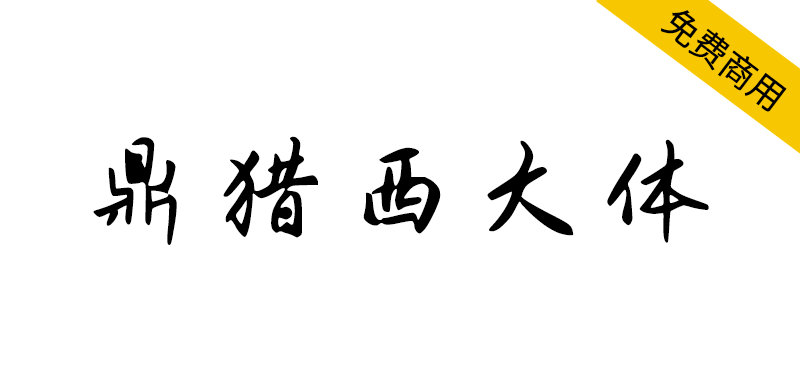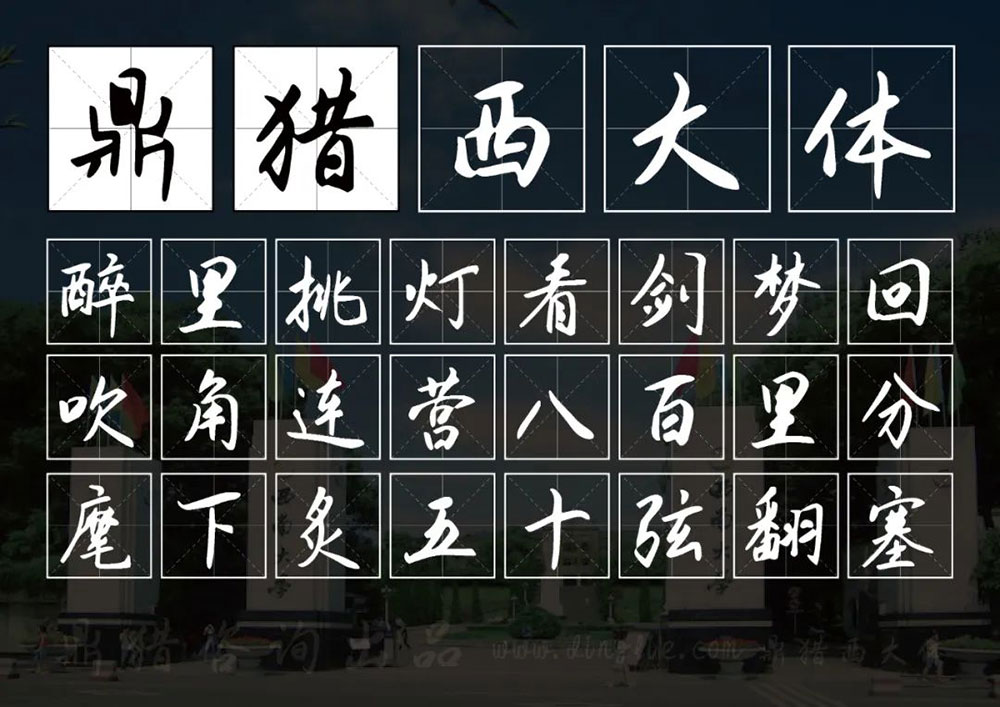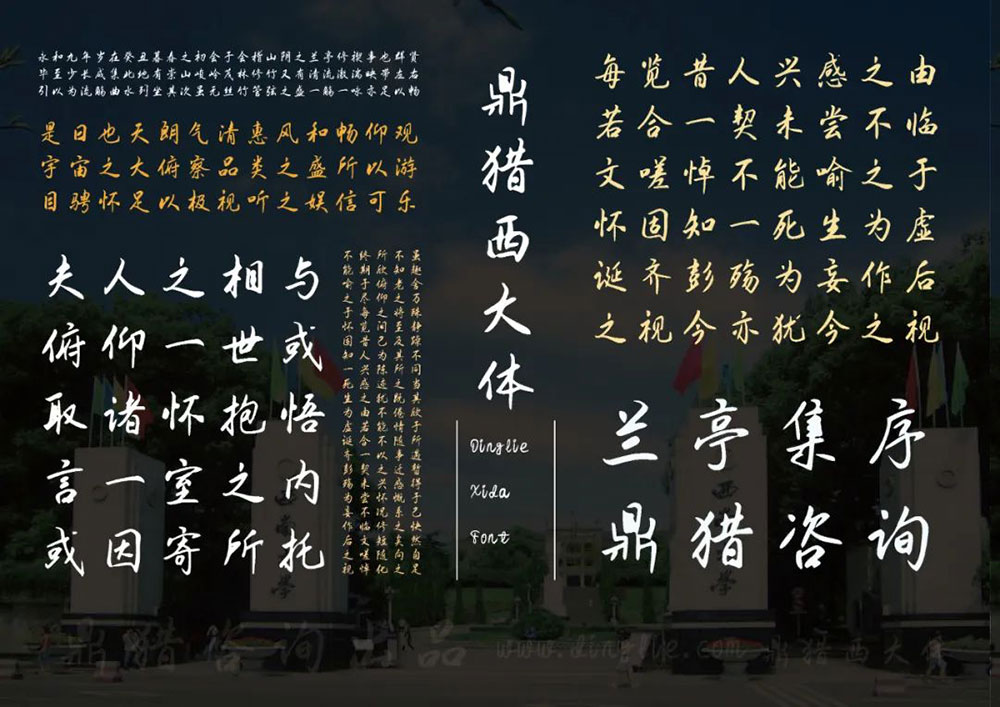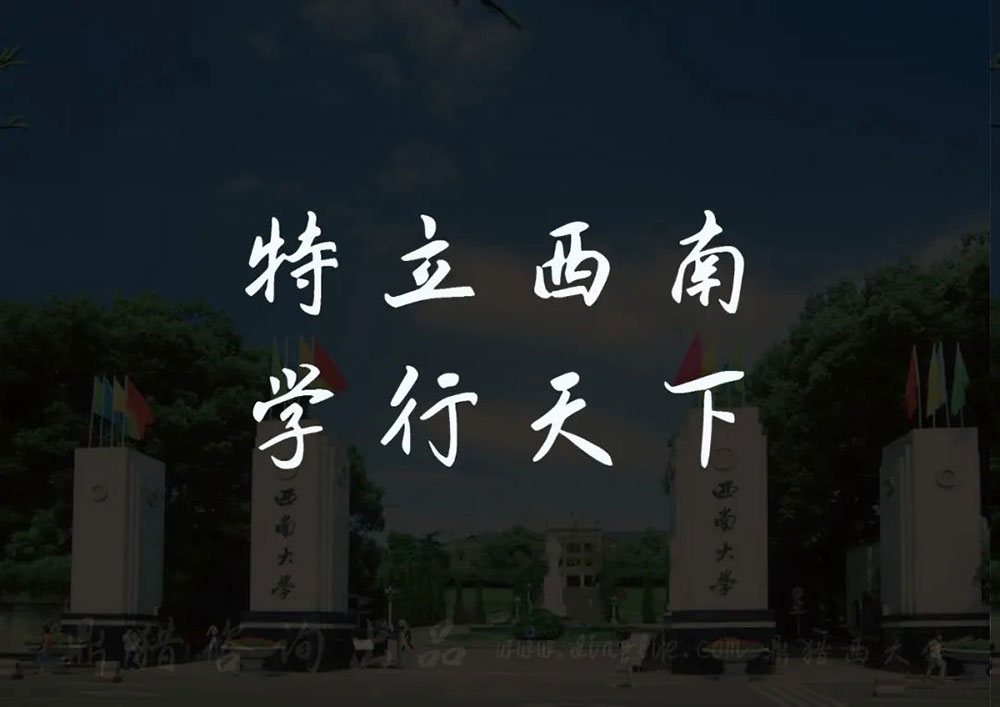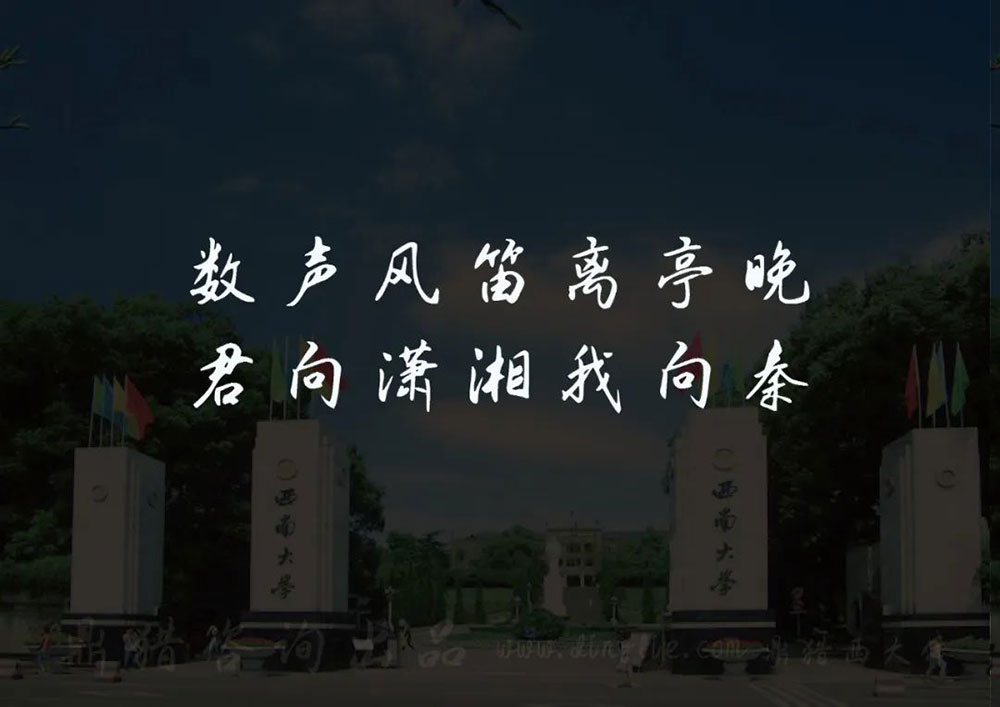
鼎猎西大体,是一款自由的手写行楷。鼎猎西大体以作者母校简称命名,追忆恰同学少年。鼎猎西大体并不完美,就像是我们总有些遗憾的青葱校园岁月,也像我们总有些力所不逮的烟火生活。可,岁月悠悠,学海茫茫,人海茫茫。我们依旧载满美好的回忆与憧憬。鼎猎西大体排版时自由肆意,版式洒脱无拘,适合美食餐饮、文化艺术展览、企业文化,以及封面杂志海报、餐饮茶饮、美妆护肤等各个行业。